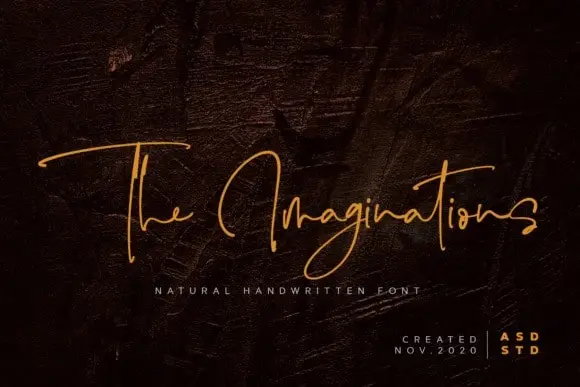
The Imaginations Handwritten Font – Download Grátis
A Imaginations Handwritten Font é inspirada nas assinaturas que transformam a escrita num elemento único e interessante. Com seu estilo elegante e pessoal, essa fonte criada pela Asd Studio está ideal para uma variedade de campos de design como anúncios de eventos, promoções de produtos, títulos de livros, títulos de atividades, logomarcas e mais. Quando combinada com tipos serifados, ela pode tornar seu projeto visualmente mais atraente e perfeito. Seja para um evento especial ou para uma marca que representa sua empresa, essa fonte é ideal para quem busca algo único e autêntico.